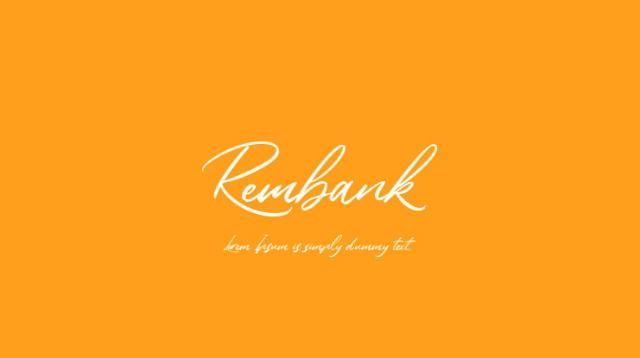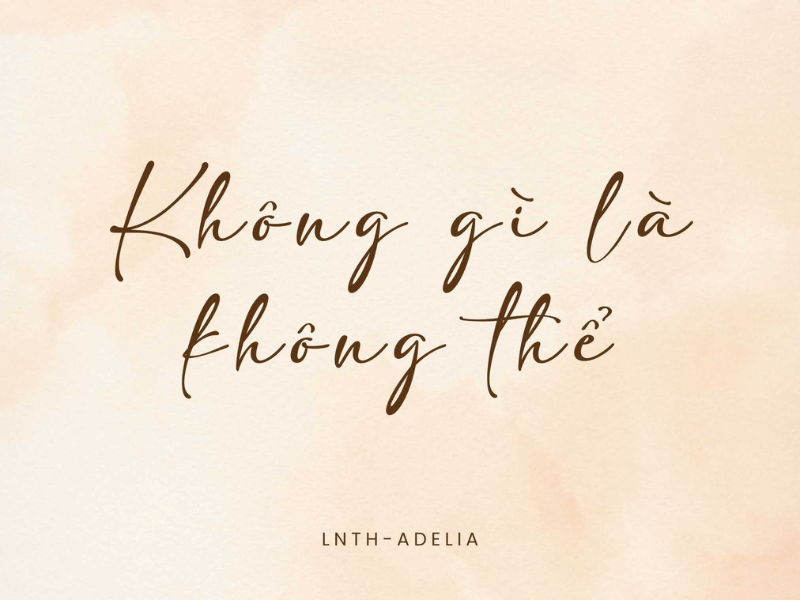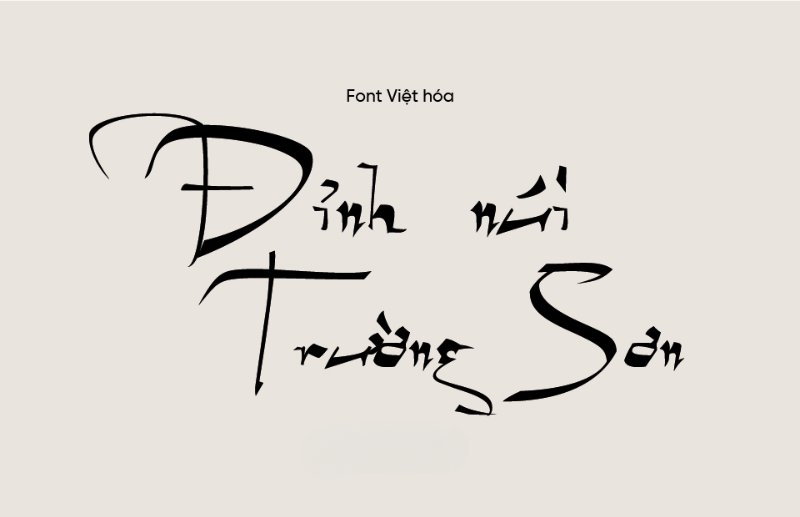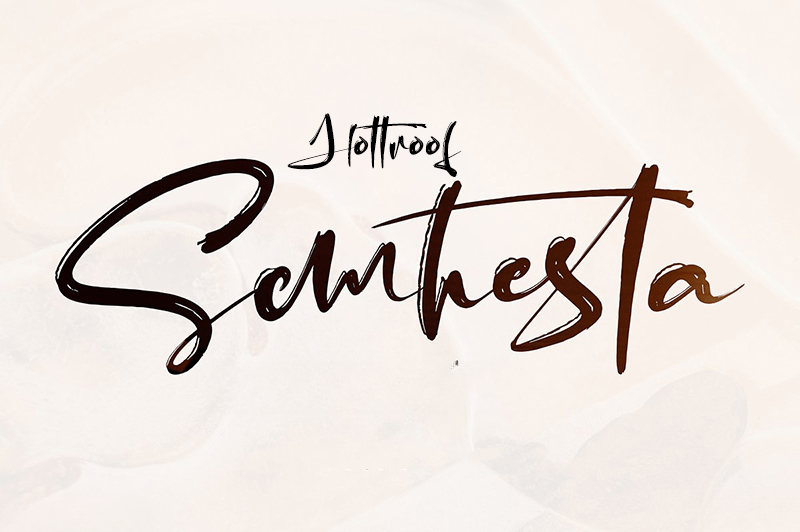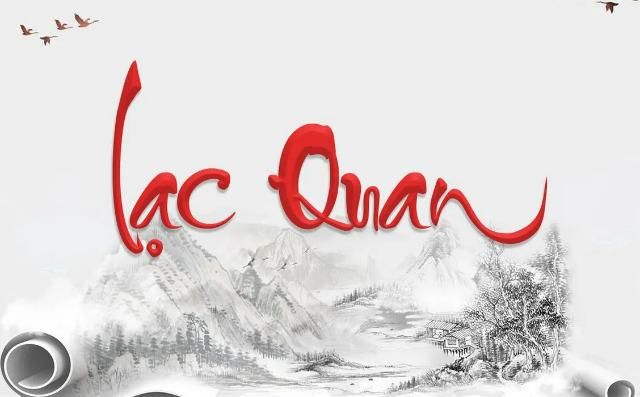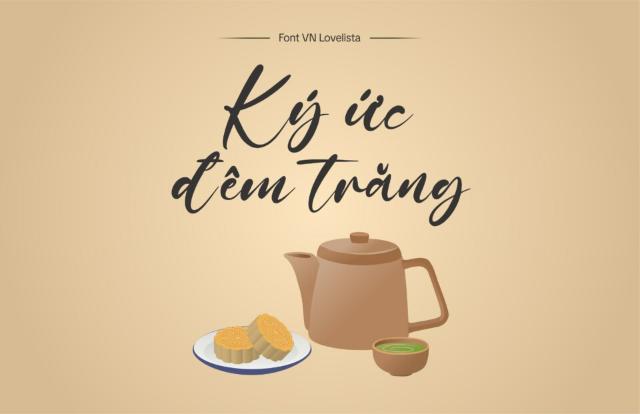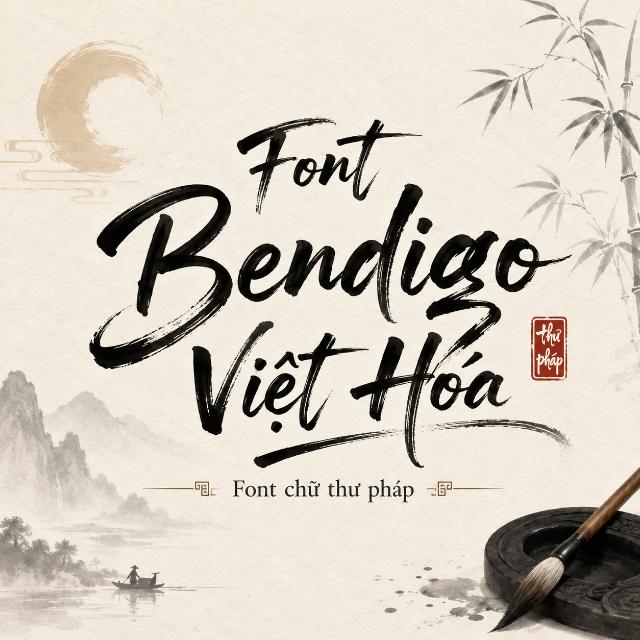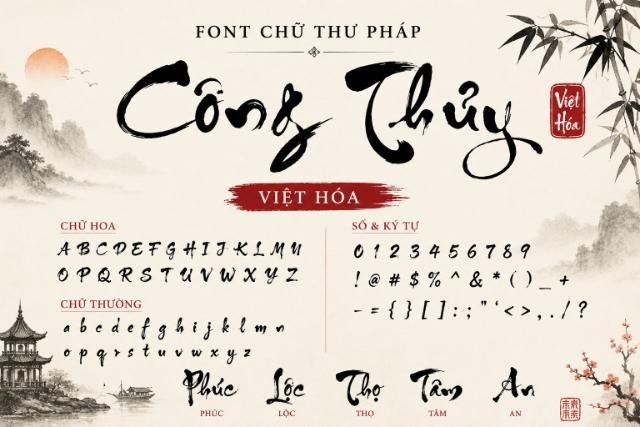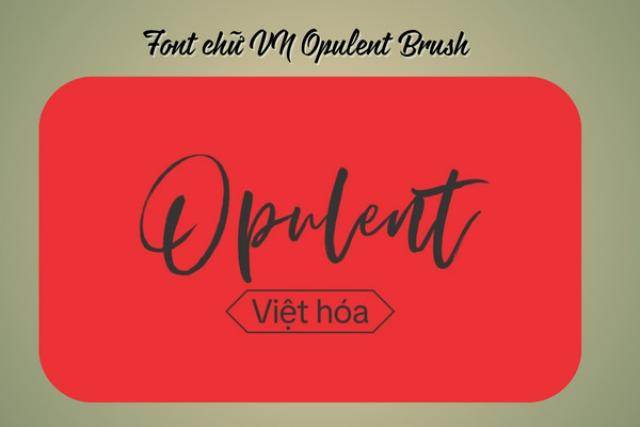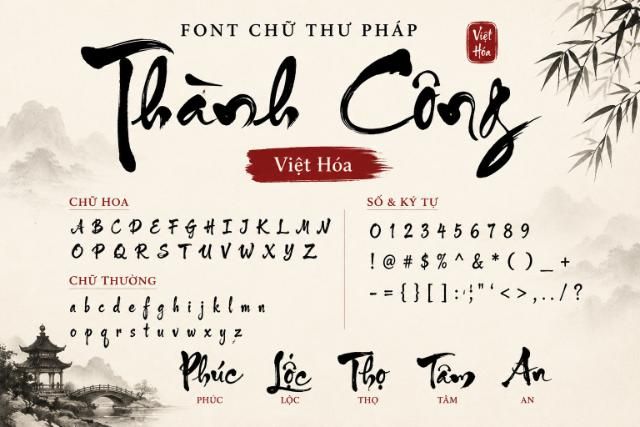
10+ Font chữ thư pháp việt hóa đẹp nhất, không lỗi dấu (Cập nhật 2026)
Bạn đang cần thiết kế thiệp Tết, lịch xuân, bao bì sản phẩm, tranh dân gian hay các ấn phẩm mang phong cách truyền thống Việt Nam? Font chữ thư pháp luôn là lựa chọn lý tưởng để tạo cảm giác mềm mại, nghệ thuật và đậm chất Á Đông. Tuy nhiên, không ít designer gặp cảnh tải font về nhưng gõ tiếng Việt bị lỗi dấu, chữ biến thành ô vuông hoặc hiển thị sai nét, khiến quá trình thiết kế mất rất nhiều thời gian chỉnh sửa.
Font chữ thư pháp là gì? Sức hút trong thiết kế đương đại
Font chữ thư pháp (Calligraphy font) thực chất là nghệ thuật typography mô phỏng lại đường nét uyển chuyển của bút lông và cọ mực truyền thống. Thay vì mài mực, vẩy cọ trên giấy xuyến chỉ như các ông đồ xưa, bạn giờ đây có thể tạo ra những nét chữ “rồng bay phượng múa” ngay trên các phần mềm đồ họa.
Sức hút mãnh liệt của dòng font này nằm ở khả năng thổi hồn văn hóa Á Đông vào ấn phẩm kỹ thuật số. Giữa một rừng các phông chữ hiện đại đôi khi hơi khô khan, nét cọ xước đầy ngẫu hứng lập tức đánh thức cảm giác hoài niệm, sang trọng và mang đậm tính độc bản.
Đây chính là “vũ khí bí mật” giúp các designer chinh phục những khách hàng khó tính nhất. Dưới đây là những dự án thực tiễn mà bộ font này sẽ phát huy tối đa sức mạnh:
• Thiết kế bao bì sản phẩm cổ truyền: Nâng tầm giá trị thương hiệu cho các hộp trà đạo cao cấp, vỏ hộp bánh mứt, hay nhãn mác của những chai rượu nếp ủ lâu năm.
• Ấn phẩm sự kiện và mùa lễ hội: Tạo điểm nhấn thị giác hoàn hảo cho thiệp cưới truyền thống, thiệp chúc Tết doanh nghiệp, hay những ấn phẩm câu đối đỏ rực rỡ ngày xuân.
• Thiết kế đồ họa nghệ thuật: Ứng dụng xuất sắc khi làm typography cho tranh mộc bản, thiết kế poster triển lãm văn hóa, hoặc tạo ra các bức tranh sơn mài decor không gian sống mang vẻ đẹp tĩnh tại, thiền định.
Khám phá các bộ Font Chữ Thư Pháp Việt Hóa được ưa chuộng nhất
Việc chọn đúng mặt chữ quyết định đến 80% cảm xúc của người xem ngay từ ánh nhìn đầu tiên. Quá trình chọn lọc và việt hóa font đòi hỏi sự am hiểu typography sâu sắc để giữ nguyên thần thái của nét cọ gốc.
Sau nhiều năm thực chiến trong ngành thiết kế, chúng tôi đã sàng lọc ra những “viên ngọc sáng” mang tính ứng dụng cao nhất. Dưới đây là các ứng cử viên chắc chắn bạn sẽ cần lưu lại cho dự án sắp tới:
• Font VN Lovelista: Mang đậm chất lãng mạn với các đường nét thanh mảnh, bay bổng. Đây là lựa chọn hoàn hảo khi bạn thiết kế thiệp chúc xuân hoặc các ấn phẩm mang sắc thái nhẹ nhàng.
• Font VN Opulent Brush: Trái ngược với sự mềm mại, bộ font này mô phỏng nét cọ lớn, dứt khoát. Cực kỳ hiệu quả để làm tiêu đề chính (Headline) thu hút sự chú ý cho các chiến dịch truyền thông dịp Tết.
• Font Bendigo Việt Hóa: Sự pha trộn tinh tế giữa nét cọ cổ điển và nhịp điệu typography hiện đại. Các nét xước được xử lý khéo léo, không gây rối mắt ngay cả khi in trên bao bì kích thước nhỏ.
• Font LNTH Watermark: Nếu bạn đang tìm kiếm hiệu ứng mực loang trên giấy xuyến chỉ chân thực nhất, đây là câu trả lời. Font chữ mang lại cảm giác mộc mạc, đậm chất hoài cổ Á Đông.
• Font LNTH Dieter Steffmann: Sở hữu cấu trúc chữ khá chuẩn mực và dễ đọc. Phù hợp cho những đoạn văn bản ngắn, câu đối cần sự trang trọng nhưng vẫn giữ trọn vẹn nét nghệ thuật truyền thống.
Để thiết kế các sản phẩm nghệ thuật mang tính độc bản cao hơn, bạn sẽ cần những typeface chuyên biệt. Hãy bổ sung ngay các bộ font đậm chất văn hóa Việt sau vào thư viện của mình:
• Font Thành Công: Được giới designer mệnh danh là “chữ ông đồ thời số”. Font mô phỏng chính xác lối viết thư pháp Việt với các nét móc, phẩy đặc trưng, tuyệt vời cho thiết kế bao bì mứt Tết, hộp trà đạo.
• Font MTD Geza Script: Cực kỳ linh hoạt và sang trọng. Bộ font này xuất hiện dày đặc trên các ấn phẩm quảng cáo cao cấp nhờ sự cân bằng hoàn hảo giữa tính thẩm mỹ và độ rõ nét.
• Font SVN Hottroof Semhesta: Mang nhịp điệu nhanh, dồn dập như những nét vẩy cọ đầy ngẫu hứng. Rất phù hợp cho các thiết kế poster triển lãm cần sự phá cách và ấn tượng thị giác mạnh.
• Font Tiểu Tự: Sở hữu những nét mảnh mai, tinh xảo tuyệt đối. Rất lý tưởng khi bạn cần một typeface để chèn những câu thơ tĩnh tâm lên các tác phẩm tranh sơn mài nghệ thuật, hay các ấn phẩm truyền thông cho không gian tinh tế như Artnam Gallery.
• Font Công Thủy: Đúng như tên gọi, các đường nét uyển chuyển, mềm mại như nước chảy. Thích hợp để làm điểm nhấn typography trên các sản phẩm decor mang hơi hướng thiền định.
Việc chọn đúng font chữ thư pháp sẽ thổi hồn vào các thiết kế, giúp tác phẩm mang đậm hơi hướng văn hóa và truyền thống.